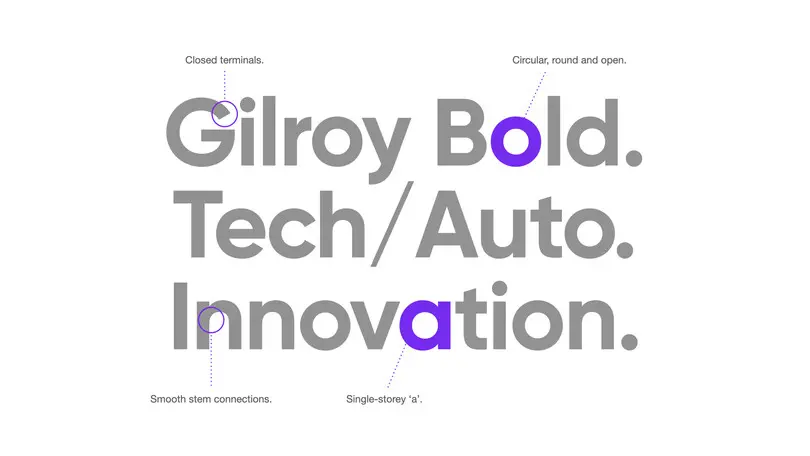
¿No das con la tipografía perfecta? Te contamos qué hacer.
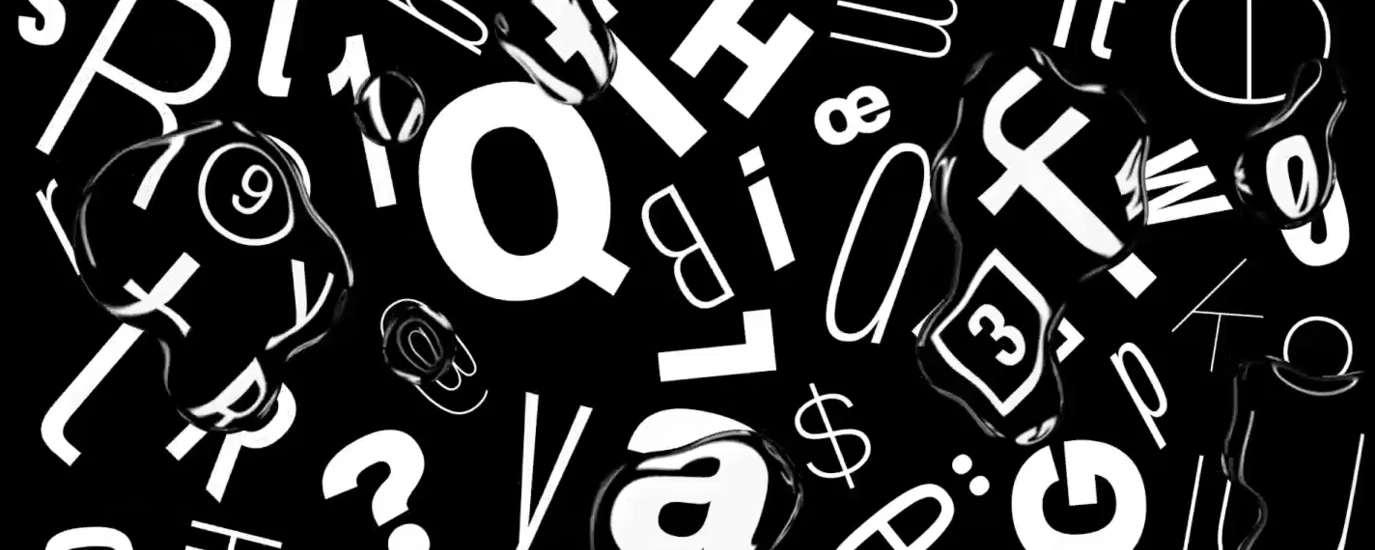
Otra vez en el mismo punto: estás en tu escritorio y toca empezar un nuevo proyecto de diseño. Lo primero: elegir una tipografía. Abres la lista de fuentes online y enseguida te sientes bombardeado por la cantidad de opciones. La oferta de tipografías es abrumadora. Después de varias horas investigando, por fin das con una familia que te gusta, pero no estás seguro de cómo se verá en móvil. Saltas a otra opción, pero dudas de si encajará con tu público objetivo.
Antes de que te des cuenta, lo que ha empezado como una búsqueda rápida se convertirá en una tarde entera de análisis de fuentes. Al acabar el día, quizás hayas podido reducir la lista de opciones a unas diez fuentes, pero sigues sin quitarte de encima la sensación de que te falta algo. Y es que quieres elegir el tipo de fuente perfecta para tu marca. ¿Cuál es el siguiente paso?
Como profesionales del diseño, reducir las opciones de fuentes entre todas las tipografías que hay es una de las tareas más difíciles a las que nos enfrentamos a la hora de poner en marcha un nuevo proyecto. Seleccionar la fuente perfecta para una marca es todo un reto. Ya sea una campaña, el lanzamiento de un producto o una renovación de marca, la tipografía que elijas es importante, ya que puede influir en la respuesta de los consumidores y las consumidoras. De hecho, puedes generar un 13 % más de respuestas positivas si das con la tipografía correcta.
La tipografía puede generar una sensación de confianza y causar un impacto duradero en el público. La tipografía solo es uno de los muchos ingredientes que componen un diseño; la identidad visual de la marca debe tener unas bases sólidas. Recuerda que desarrollar una identidad de marca coherente puede incrementar los ingresos en un 33 %.
Precisamente para lograr esa coherencia de marca, es necesario elegir una fuente que pueda funcionar en todas las plataformas, por lo que dar con una familia de fuentes polivalente es fundamental. ¿No sabes cómo elegir la tipografía adecuada? Realmente, las decisiones que se toman en el proceso de diseño son subjetivas, por lo que el propio concepto de «tipografía perfecta» también lo es. Desde nuestro punto de vista, la elección de la fuente se basa en un 50 % en el aspecto y en un 50 % en lo que nos satisface la decisión. Dicho esto, ¿cómo puedes tener la certeza de estar eligiendo la fuente adecuada para tu proyecto?
La cantidad de opciones puede ser abrumadora. Si te bloqueas, da un paso atrás y hazte algunas preguntas clave:
- ¿Qué objetivos quieres conseguir con la tipografía?
- ¿Quién es el público objetivo al que quieres llegar?
- ¿Qué tipo de identidad de marca quieres construir?
- ¿Qué futuro visual prevés para tu marca?
Plantearte estas preguntas clave te ayudará a pensar en formas de alcanzar los objetivos de tu proyecto gracias a las decisiones que tomes sobre la identidad de la marca. Durante el proceso, no te olvides de la funcionalidad. Debes tener en cuenta la accesibilidad, la legibilidad y la conexión emocional de la fuente que elijas. Al fin y al cabo, la tipografía más legible se lee un 33,1 % más rápido que la menos legible. Cuando se tiene poco tiempo para causar una buena primera impresión, la legibilidad es crucial.
Recurre al mapa de cuadrantes para definir la percepción.
Una opción para encontrar el tipo de fuente adecuada es recurrir a los cuadrantes de percepción, un modelo que te ayudará a entender las fuentes que encajan con las marcas. En cada punto del eje, cada uno de los cuadrantes se etiqueta con una palabra clave que define el posicionamiento de la marca (por ejemplo, tradicional o moderna). En esos cuadrantes, debes colocar ejemplos de fuentes para determinar su percepción.
Una forma práctica de entender qué tipografías encajan mejor con tu marca es trabajar con cuadrantes de percepción. Se traza un eje con valores (tradicional/moderno, formal/informal, etc.) y se colocan ejemplos de tipografías en cada cuadrante. Este ejercicio ayuda a identificar qué fuentes transmiten mejor la personalidad de la marca y también a experimentar con combinaciones tipográficas: quizá necesites una tipografía potente para grandes formatos y otra más ligera para móvil. Lo importante es que las fuentes funcionen bien juntas y estén alineadas con los valores centrales de la marca.
Utiliza bibliotecas de fuentes.
Otra fuente de inspiración para seleccionar un tipo de letra son las bibliotecas de fuentes, en las que puedes filtrar las opciones fácilmente en función del posicionamiento de marca. En lugar de rebuscar entre infinitas opciones de fuentes, puedes afinar tu búsqueda con filtros para acotar lo que te ofrece una biblioteca de fuentes fiables y de alta calidad. A veces menos sí que es más. A medida que vayas refinando tu selección de fuentes, no te olvides de comprobar el tiempo de carga de la página, la facilidad de lectura de la fuente y la accesibilidad para los usuarios y usuarias. Debes asegurarte de que tus fuentes funcionarán en los casos de uso que necesitas. Ten en cuenta que el tiempo de carga de la página es clave: la probabilidad de rebote aumenta en un 32 % si el tiempo de carga de la página se incrementa de uno a tres segundos. Tu fuente también debe poder leerse en varios dispositivos diferentes sin latencia, la cual suele deberse a archivos de gran tamaño o a problemas de representación.
Consejos rápidos:
- Carga previamente tus fuentes y alójalas en tu propio servidor.
- Comprueba que tienes el formato de archivo más reciente, como WOFF2.
- Siempre que sea posible, usa tipografías variables: ocupan menos que una familia completa con todos los pesos.
Un muy buen ejemplo de tipo de letra variable es Cotford, una fuente contemporánea con remate, obra del director creativo de tipografía de Monotype, Tom Foley. Cotford, creada para la era digital, permite a profesionales del diseño ajustar el tipo de letra hasta dar con el grosor, el contraste y el tamaño óptico adecuados para su proyecto.
Depende de ti tomar la mejor decisión con la información de la que dispongas. Como diseñador o diseñadora, tienes en tu mano la posibilidad de ayudar a las marcas a lograr el equilibrio entre su personalidad y sus necesidades.